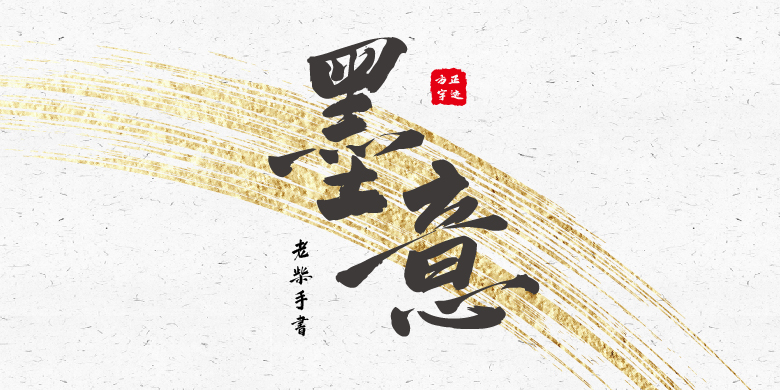
标签:书法力量中国风豪放方正字迹2019新字体毛笔 字体介绍: 方正字迹-老柴手书是一款传统书法与现代设计相结合的创意书法字体,字体苍劲有力,豪放大气,适合海报等大标题广告宣传领域。作者柴海军,小米公司设计师、小米书法协会会长。 方正字迹-老柴手书 简体 方正字跡-老柴手書繁体 方正字迹-老柴手书 品牌: 方正字迹 设计师: 柴海军 发行时间:2019 字库编码:简繁扩展(GBK)、大陆简体(GB2312-80) 分类:常规书写·毛笔 方正字迹-老柴手书字体下载地址 官网下载